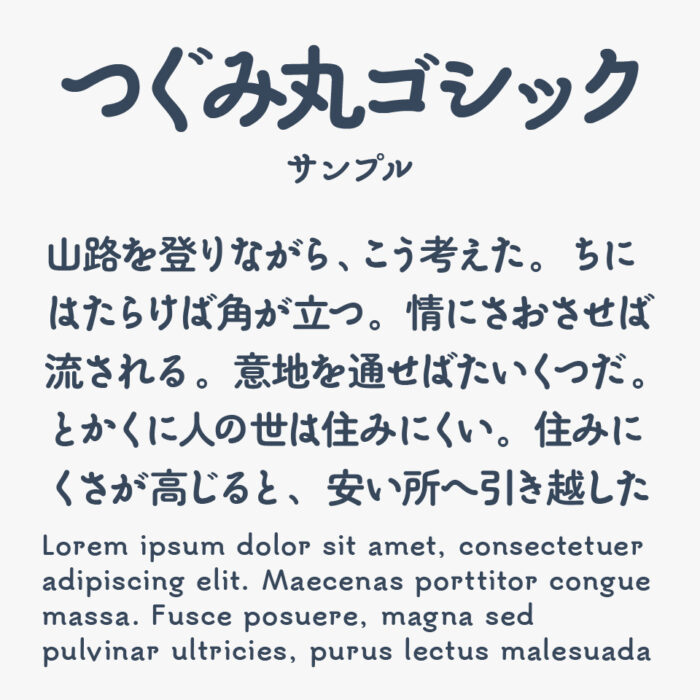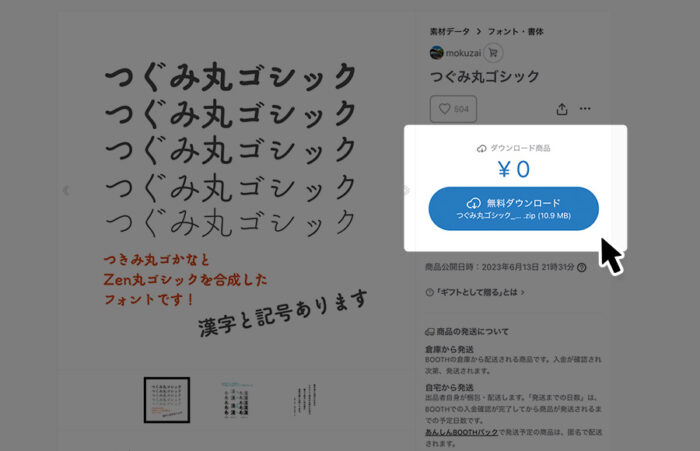
つぐみ丸ゴシックは、「つきみ丸ゴかな」と「Zen丸ゴシック」を混植して制作された読みやすさと親しみやすさのバランスが良い丸ゴシックフォントです。
かな文字の「つきみ丸ゴかな」のオールドスタイルと均整の取れた骨格に丸みを加えた、しっかりとした太さと上品な雰囲気が感じられるフォントとなっています。丸ゴシックになっていることで、そこまで堅苦しくなく、かつ崩しすぎてもないバランスのよい素敵なフォントです。